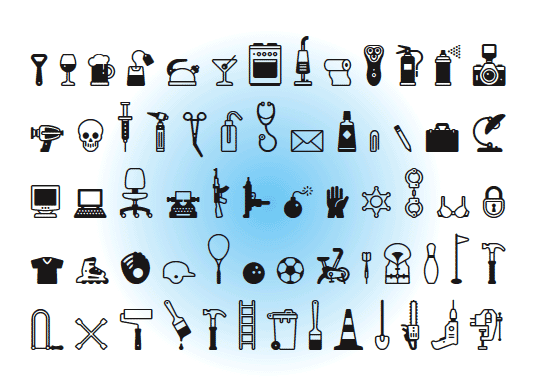
Suche Pictogramme Font
ich steh aufm Schlauch ... die Frage hört sich jetzt blöd an, aber wie heißt
der Font mit den schier unzähligen Pictogrammen. Die Pictos haben eine
weiche Anmutung und es sind auch Themengebiete wie Sex, Waffen und
Drogen vertreten ... da gibts wohl nich so viele professionelle Fonts ...
hoffentlich jemand kann mir auf die Sprünge helfen.
Meinst Du „Poppi“ von Martin Friedl? Leider habe ich kein Bild davon.
Es gibt wohl nicht so viele Picto-Fonts die auch Sex, Drogen und Waffen Icons haben,
oder etwa doch? ... nein